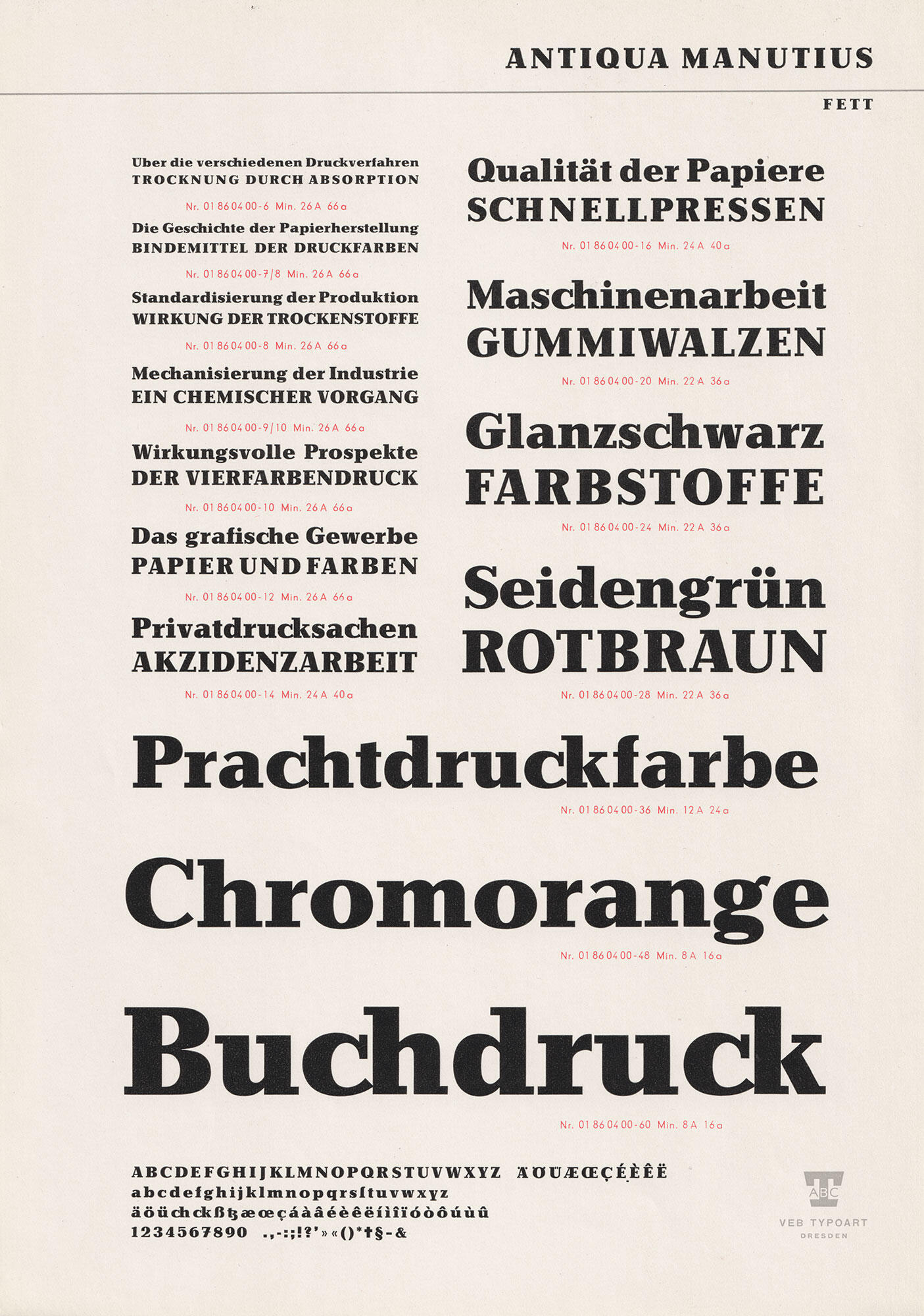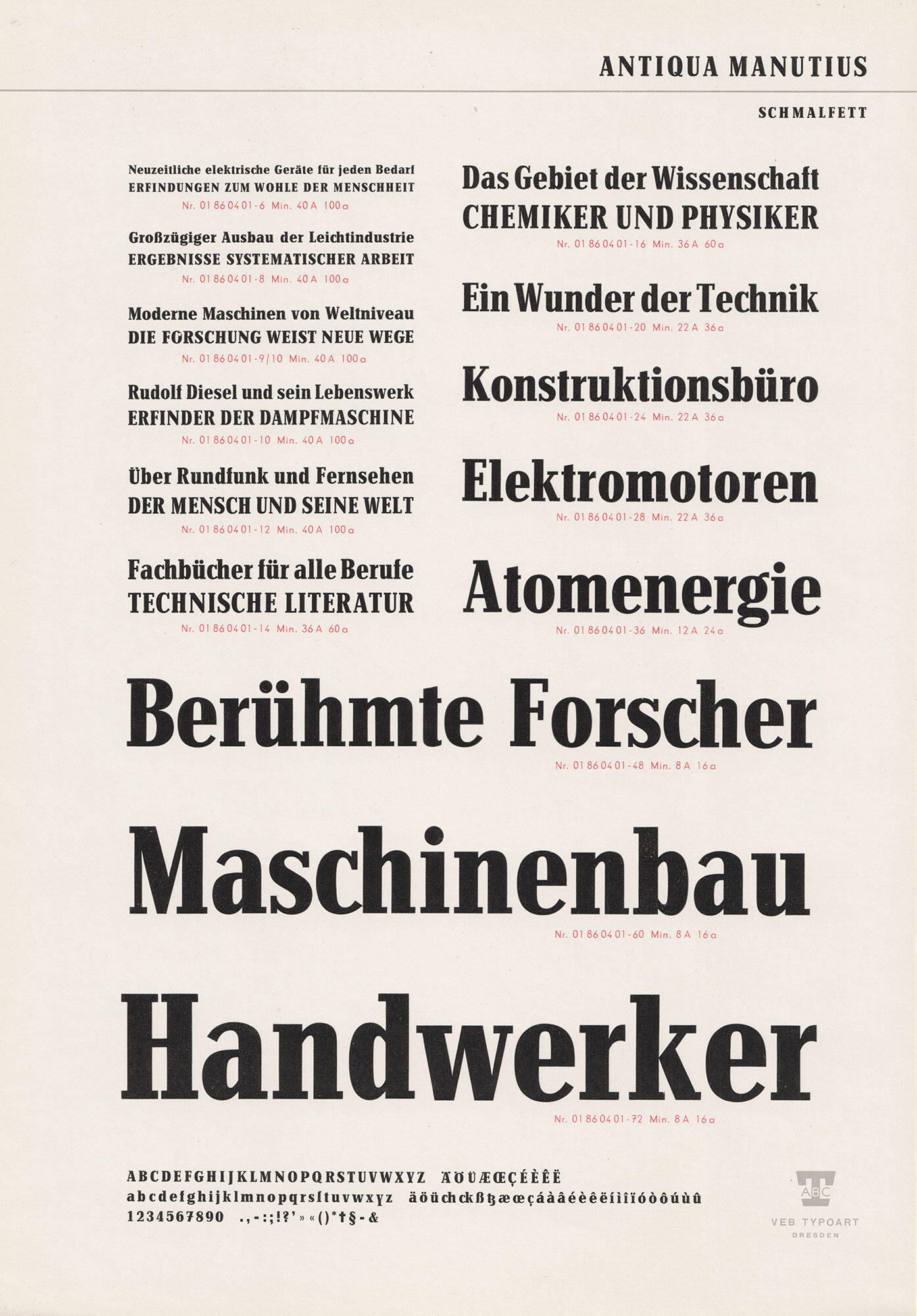
- 1950
- Antiqua statisch
Die Manutius von Arno Drescher erschien 1950 bei Schriftgießerei Ludwig Wagner in vier aufrechten Schnitten. In der Folge kam noch ein kursiver Schnitt hinzu. Nach dem Umzug der Gießerei nach Westdeutschland erschien die Schrift dort als Antiqua 505 und in Ostdeutschland als Manutius-Antiqua bei Typoart in fünf Schnitten.
Ludwig & Mayer klagten in den 1950er-Jahren gegen Ludwig Wagner, da sie die Schrift als Plagiat der Candida ansahen.
Eine Digitalisierung in vier Schnitten ist heute als Manutius Pro von RMU Fonts verfügbar.